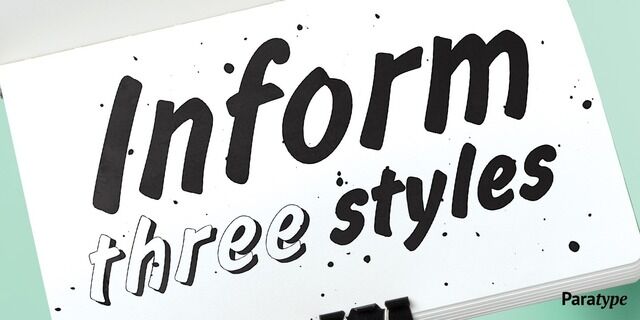
Шрифт разработан дизайнером Геннадием Барышниковым (курсивное полужирное начертание) на основе шрифта Flash, 1939 (дизайнер Эдвин Шарр). B фирме ПараТайп (ПараГраф) в 1992 к нему были разработаны дополнительные начертания (дизайнеры Владимир Ефимов, Александр Тарбеев). Шрифт основан на несвязной каллиграфии кистью. Предназначен для применения в рекламе и акциденции.